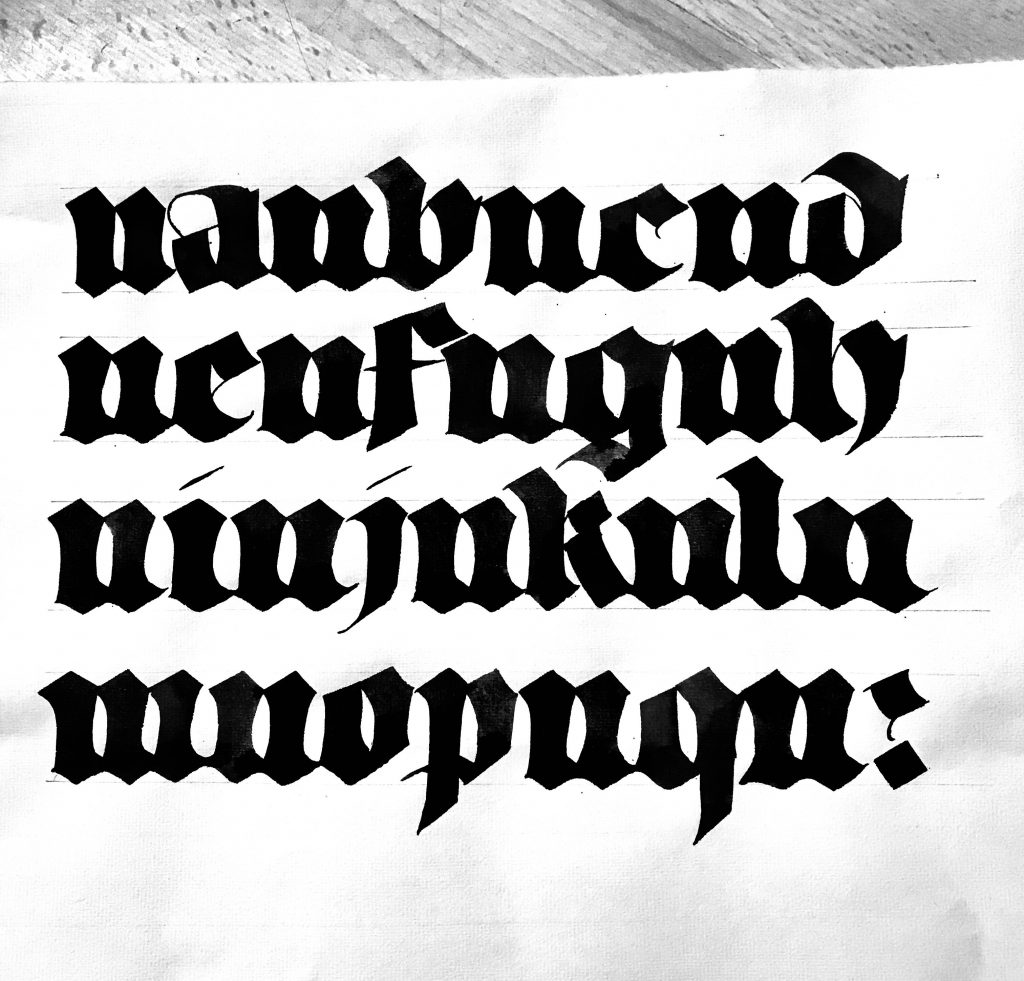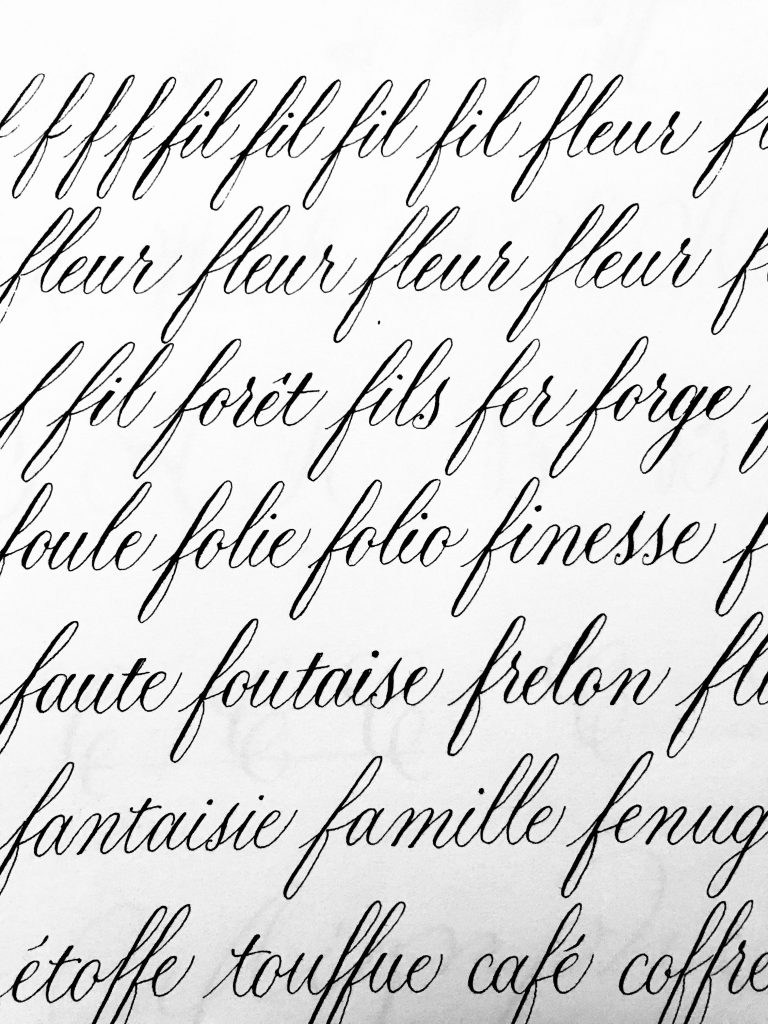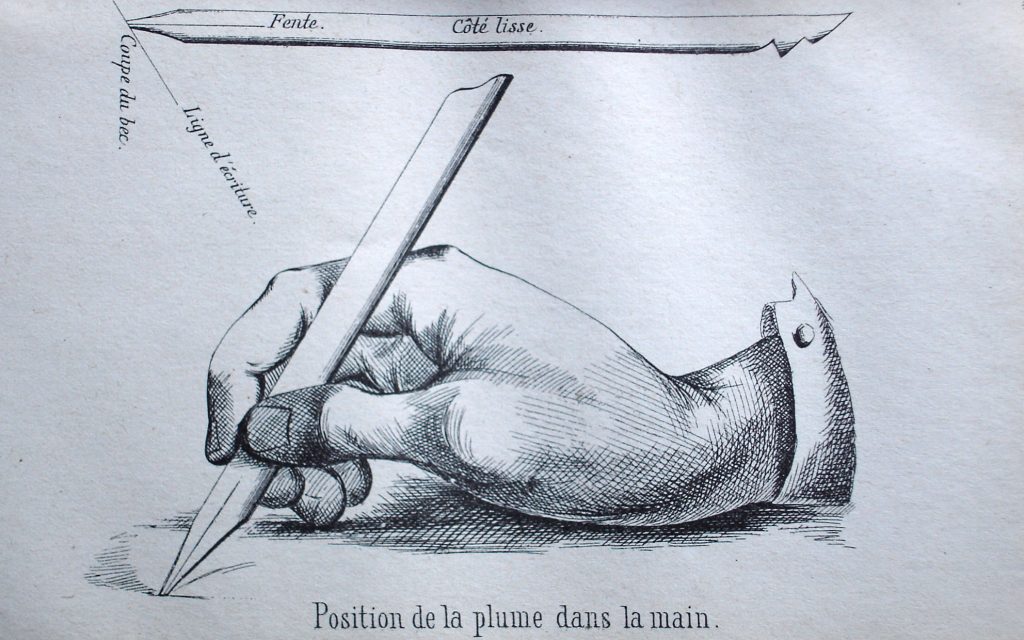
J’entends souvent que la calligraphie, c’est chouette mais que cela demande beaucoup (trop) de travail. Certes, mais quelle discipline artistique ou sportive n’en demande pas ? Pour progresser, il faut en effet travailler dur, mais surtout régulièrement. Ce n’est pas en prenant une plume tous les 10 du mois que vous allez faire de grands progrès.
Or progresser permet de soutenir notre motivation !
Apprendre et travailler en prenant du plaisir c’est possible, et même recommandé. Voici donc quelques idées – non exhaustives – pour travailler et progresser dans la joie et la bonne humeur !
1. Travailler un peu chaque jour…
…plutôt que 12h d’affilée tous les 2 mois. Comme pour l’apprentissage d’un instrument de musique ou la pratique d’un sport, un travail régulier porte de meilleurs fruits. C’est la technique des petits pas, qui assure une progression régulière. Si ce n’est pas possible de travailler un peu chaque jour, c’est pas mal de s’octroyer un ou deux créneaux dans la semaine durant lesquels on se coupe du monde et on se concentre sur la calligraphie.
2. Un petit rituel pour se mettre en condition
Je me suis rendue compte que je prends le temps de m’installer et de me préparer physiquement et mentalement. Entrer en concentration intense me demande une bonne dizaine de minutes. Pendant ce temps, j’étire mes bras, mes poignets, mes doigts; je me fais un bon gros café; je mets en marche mon diffuseur d’huiles essentielles; éventuellement je choisis une musique douce, et surtout je respire profondément. C’est également le moment de préparer son espace de travail, pour tout avoir sous la main et ne pas devoir se lever toutes les 2 minutes.
Ce faisant, le quotidien laisse place à cet espace temps exclusif, dédié à la pratique de la calligraphie. Trouvez vous aussi votre petit rituel de mise en route, ça aide à bien se centrer et à se concentrer.
3. Varier son travail
Si vous passez 2 heures à faire la même chose, à répéter strictement les mêmes gestes, votre attention risque de décroître et votre motivation de baisser. Pensez à introduire de la variété, sur une séance, et même de façon générale : essayer des variantes sur une écriture, changer de papier, de medium ou de couleurs, travailler en grand ou en petit, varier les exercices… Les possibilités sont multiples.
Pensez aussi à travailler dans une autre langue, comme l’anglais qui regorge de combinaisons de lettres (GH, TH, WH…) très intéressantes à traiter en calligraphie.
Travailler dans une autre langue : pour se concentrer sur la forme plutôt que sur le sens
4. Faire des pauses et prendre du recul
Levez la tête de la feuille, gardez l’œil ouvert, prenez de la distance et corrigez-vous… n’hésitez pas à vous corriger au stylo rouge et notez vos observations.
Se lever, faire quelques pas, permet aussi de se décrisper après l’effort.
4. Respirer
C’est bête, mais c’est tellement vrai ! Quand on se concentre on a tendance à retenir sa respiration, comme si s’immobiliser garantissait un meilleur tracé. En fait c’est tout le contraire. J’en ai déjà parlé dans un article sur l’Anglaise. Un souffle régulier, profond, aide à se concentrer, renforce la précision et la fluidité du trait.
5. Soigner sa posture
Ça c’est pour ne pas finir chez l’ostéo. Si vous êtes de la vieille école, rappelez-vous ce que disait la maîtresse au CP. On se tient droit, face à la feuille; On ne croise pas les jambes : la posture doit être stable, les 2 pieds à terre. Prendre conscience de sa respiration et de sa posture apporte beaucoup de bienfait pour le corps et l’écriture. C’est même plutôt relaxant.
« Modèle d’écriture. Dessin d’une plume arabe et sa position dans la main » in L. Machuel, Une première année d’arabe, Alger, 1877 – © Société Asiatique
7. Calligraphier des mots plutôt que d’égrener l’alphabet
Répéter des alphabets, personnellement je trouve ça mortifère. De plus ça n’apprend pas à travailler l’espacement et les liaisons. Lorsque j’ai débuté, je faisais des lettres et des lettres puis j’attaquais directement un texte. Flop assuré. Maintenant je préfère travailler assez vite sur des mots, ou des séquences de lettres même si elles ne forment pas de mots sensés (ex : MOPALE, ça ne veut rien dire mais il y a des lettres rondes, une ascendante, une descendante; Ce n’est qu’un exemple). En panne de mots ? Fleurs, fruits, pays, prénoms, villes, couleurs, animaux, adjectif… Il n’y a qu’à choisir. Pensez à un thème et laissez les mots venir !
Travailler le F en anglaise, sans faire des lignes de f-f-f-f-f-f-f….
Séquences de lettres sans sens précis, pour travailler l’espacement et la régularité
8. Se faire plaisir
Avec des petits projets, si modestes soient-ils, pour concrétiser votre travail : étiquettes, marques pages, enveloppes, cartes, carnets, petits tableaux…